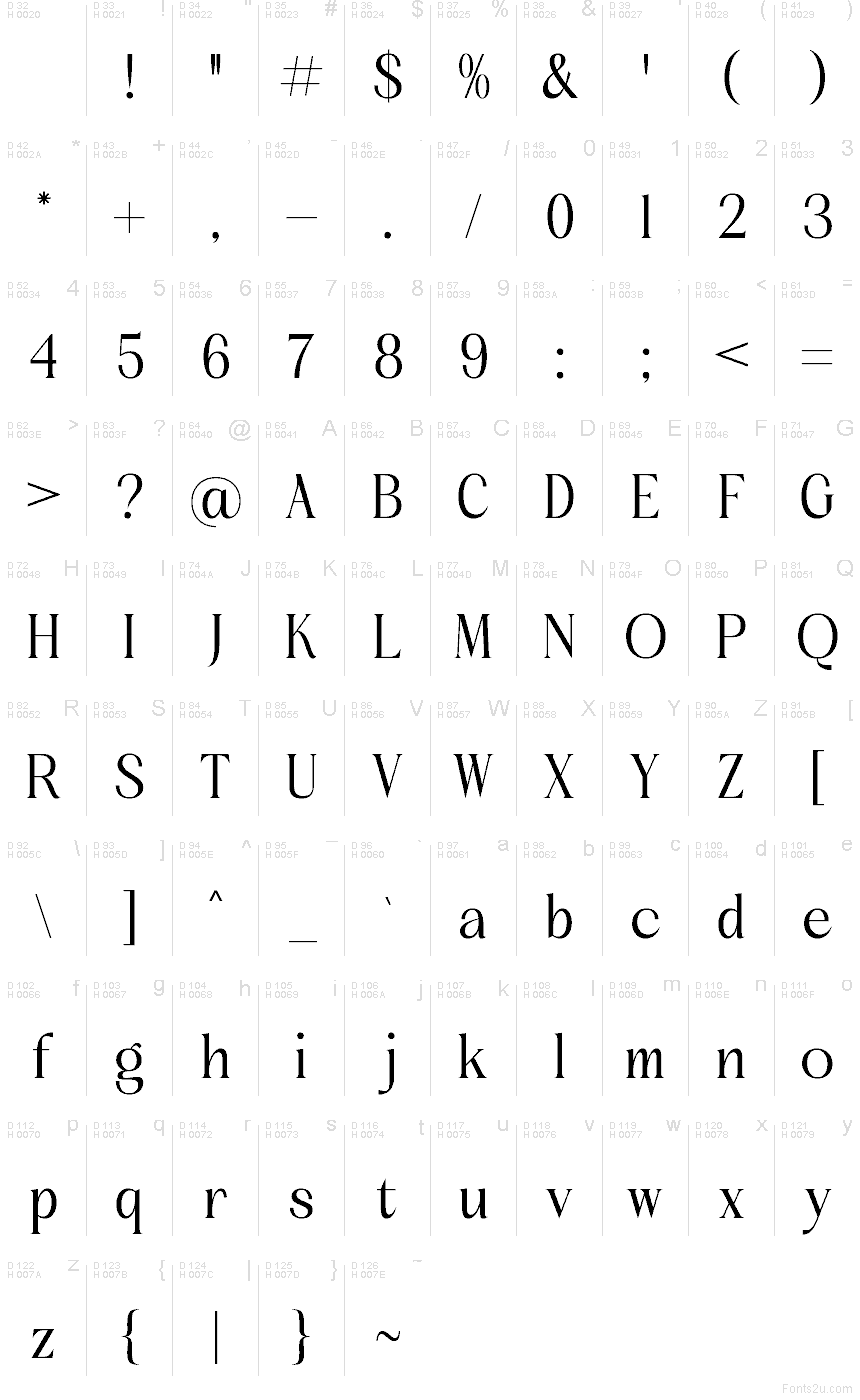
Amethast Stones de TimelessType.co est une police serif à fort contraste avec une esthétique digne d'un magazine de mode. Les lettres associent des traits longs et effilés à des jointures douces et arrondies, conférant à la police une élégance raffinée sans rigidité, rappelant davantage la typographie classique des magazines que la gravure formelle.
Elle est parfaite pour le branding de beauté, les packagings boutique, les couvertures de livres, les titres d'affiches et les logotypes élégants où quelques grands mots suffisent à créer l'ambiance. En tant que police gratuite, elle est également idéale pour les accroches, les titres d'invitations et les courtes citations, car le mélange de contraste vertical marqué et de courbes douces apporte une touche de poésie et un aspect luxueux, même aux textes les plus brefs.